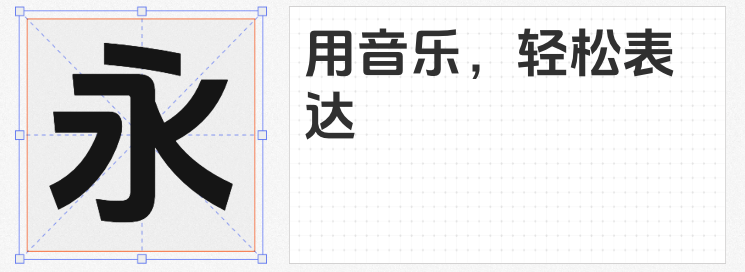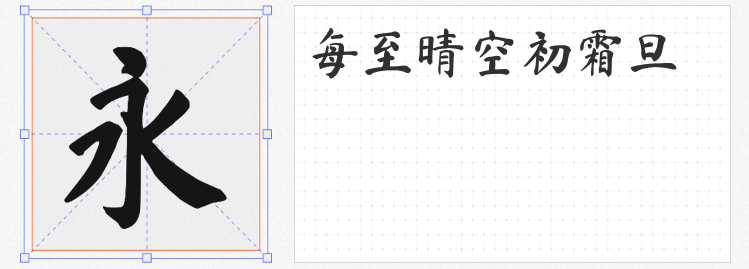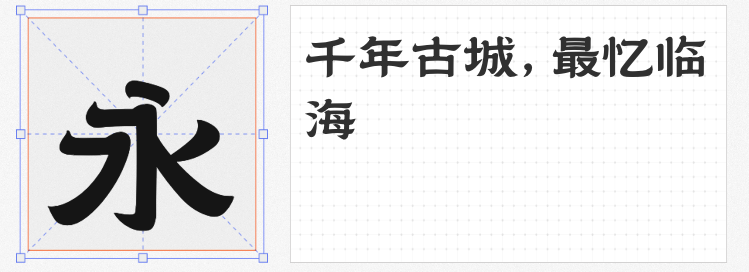
在城市宣传设计中,合适的字体能精准传达城市特色与气质。今天为大家推荐四款免费商用且端庄大气的字体,助力城市宣传大放异彩。
临海隶书由临海市与乡立方团队携手打造,承载着临海独特风格与时代烙印。其字形极具古典韵味,完美保留了隶书特点。笔画舒展,横画蚕头燕尾特征明显,竖画刚劲有力,撇捺飘逸洒脱。在城市宣传里,它能为画面增添浓厚的历史文化氛围,尤其适合展现临海这类具有深厚文化底蕴的城市,让观众一眼便能感受到城市的古朴与典雅。
阿里妈妈刀隶体通过机器学习爨宝子碑精髓,融合了隶书与楷书的特点。它强调三角点折弯与横画两端“雁尾”的方强,外露锋芒,彰显坚实、朴茂、稚拙、倔犟之感。结构大胆,布白和中宫常常出人意料,险中求正,动中求静。这种独特的风格能为城市宣传带来强烈的视觉冲击,适合表现城市独特的个性和不羁的精神,让宣传作品在众多作品中脱颖而出。
玄冬楷书是基于开源字体「马善政毛笔楷书」拓展而来,在原版基础上修复错误字形并添加竖排排版特性。它保留了楷书的端庄秀丽,笔画规范工整,结构严谨。无论是横排还是竖排,都能呈现出整齐美观的效果。在城市宣传的文本排版中,玄冬楷书能确保信息清晰易读,同时又不失文化内涵,是宣传文案排版的优质选择。
抖音美好体 Bold由抖音体验设计中心与方正字库联合设计开发。它并非常规黑体,笔画转折处采用圆角处理,简洁大方、清晰易读,兼具现代气质与人文属性。在城市宣传中,若想营造现代感又不失人文温度,这款字体是绝佳之选。它能让宣传作品紧跟时代潮流,吸引年轻受众的目光,展现城市的活力与包容。
这四款字体各具特色,在城市宣传设计中合理运用,定能为城市形象增色不少。